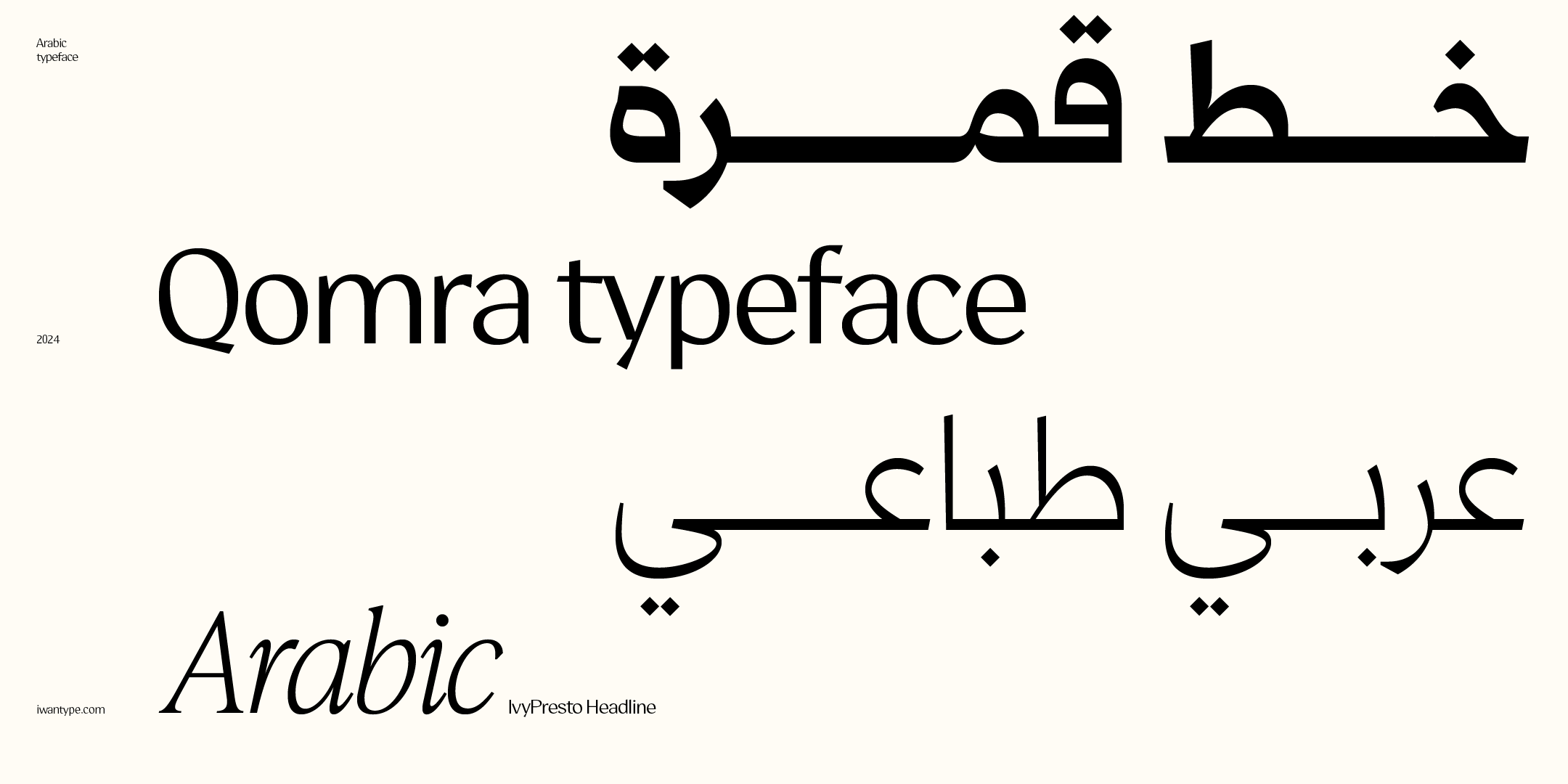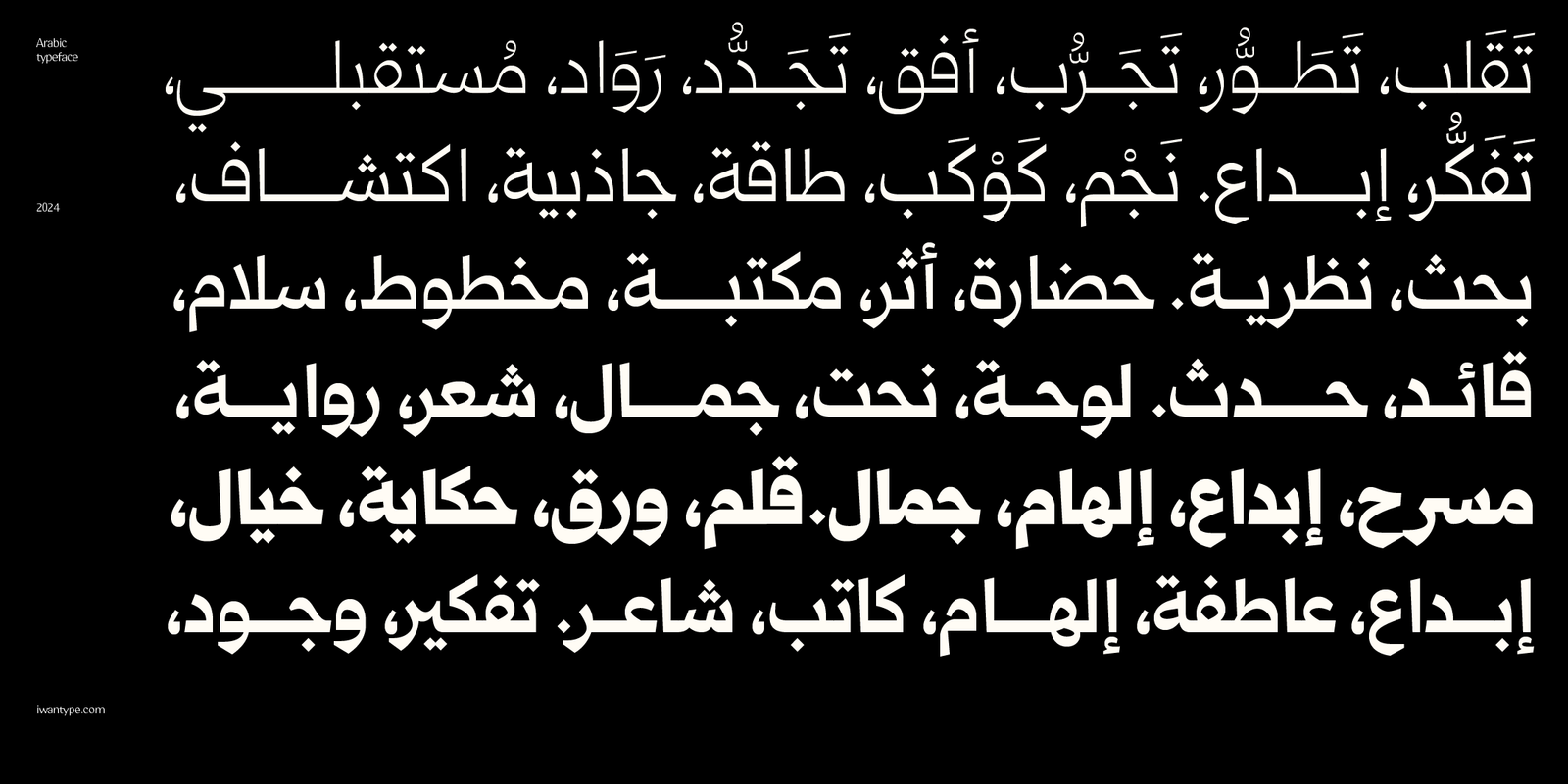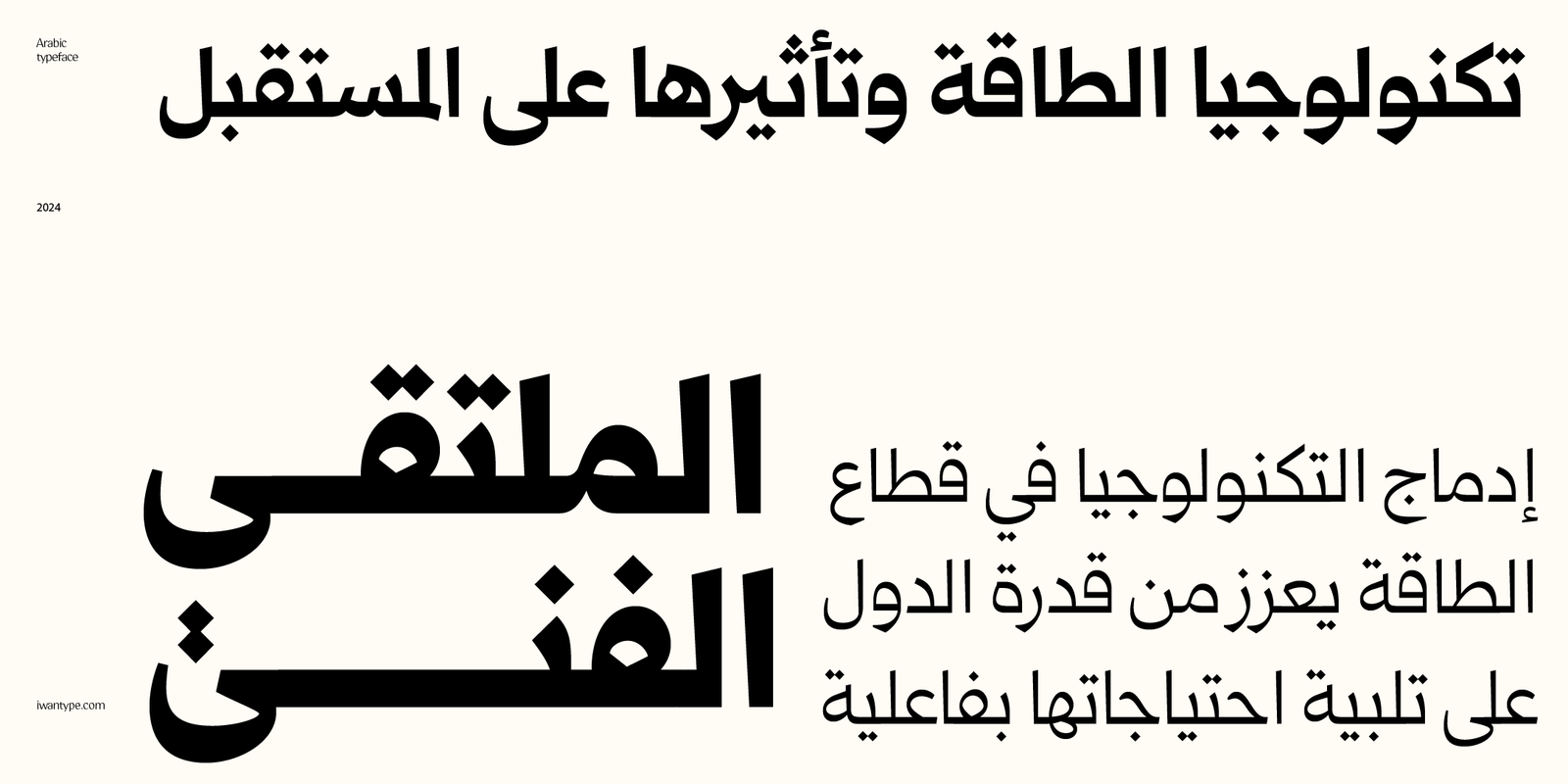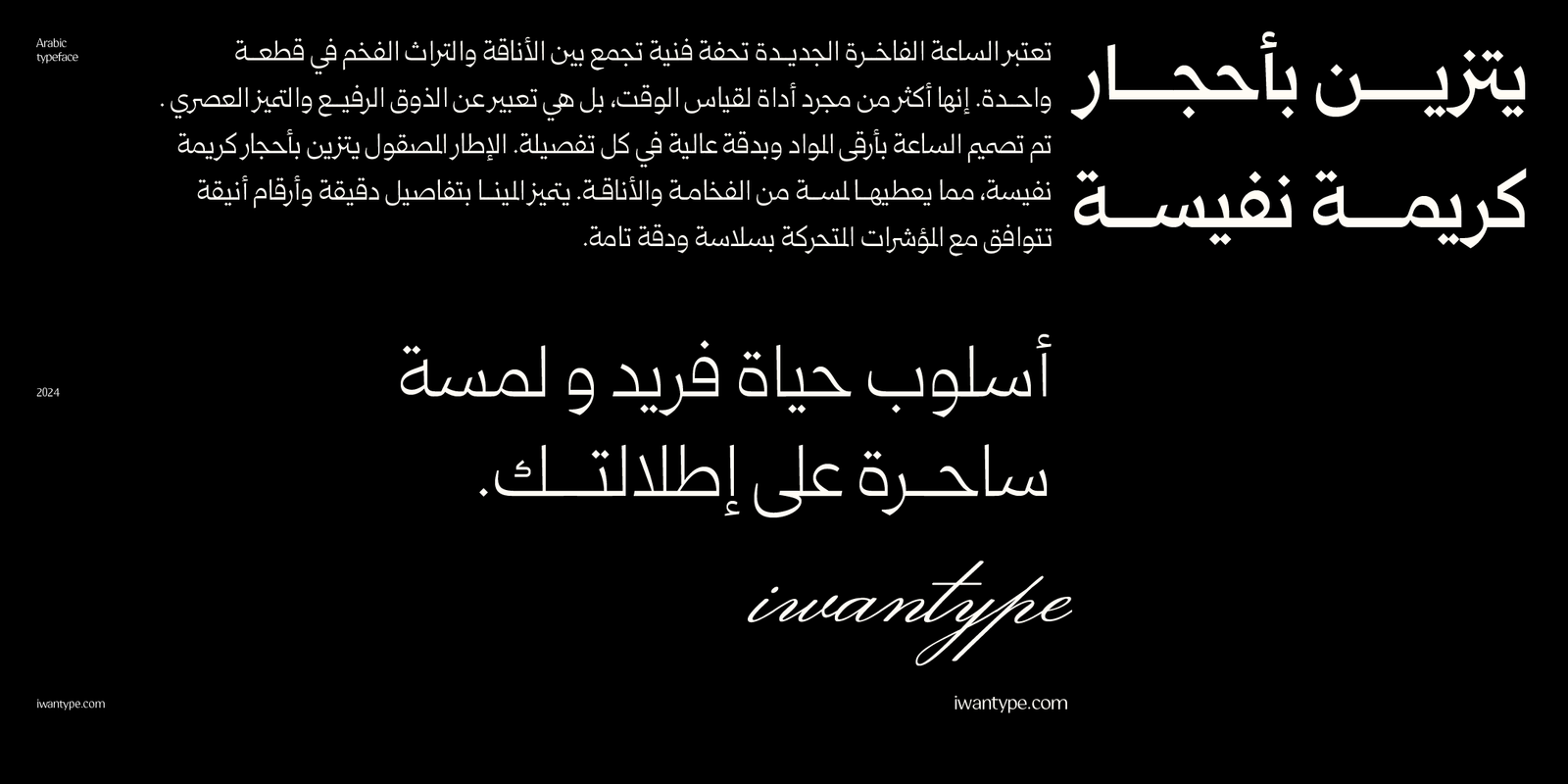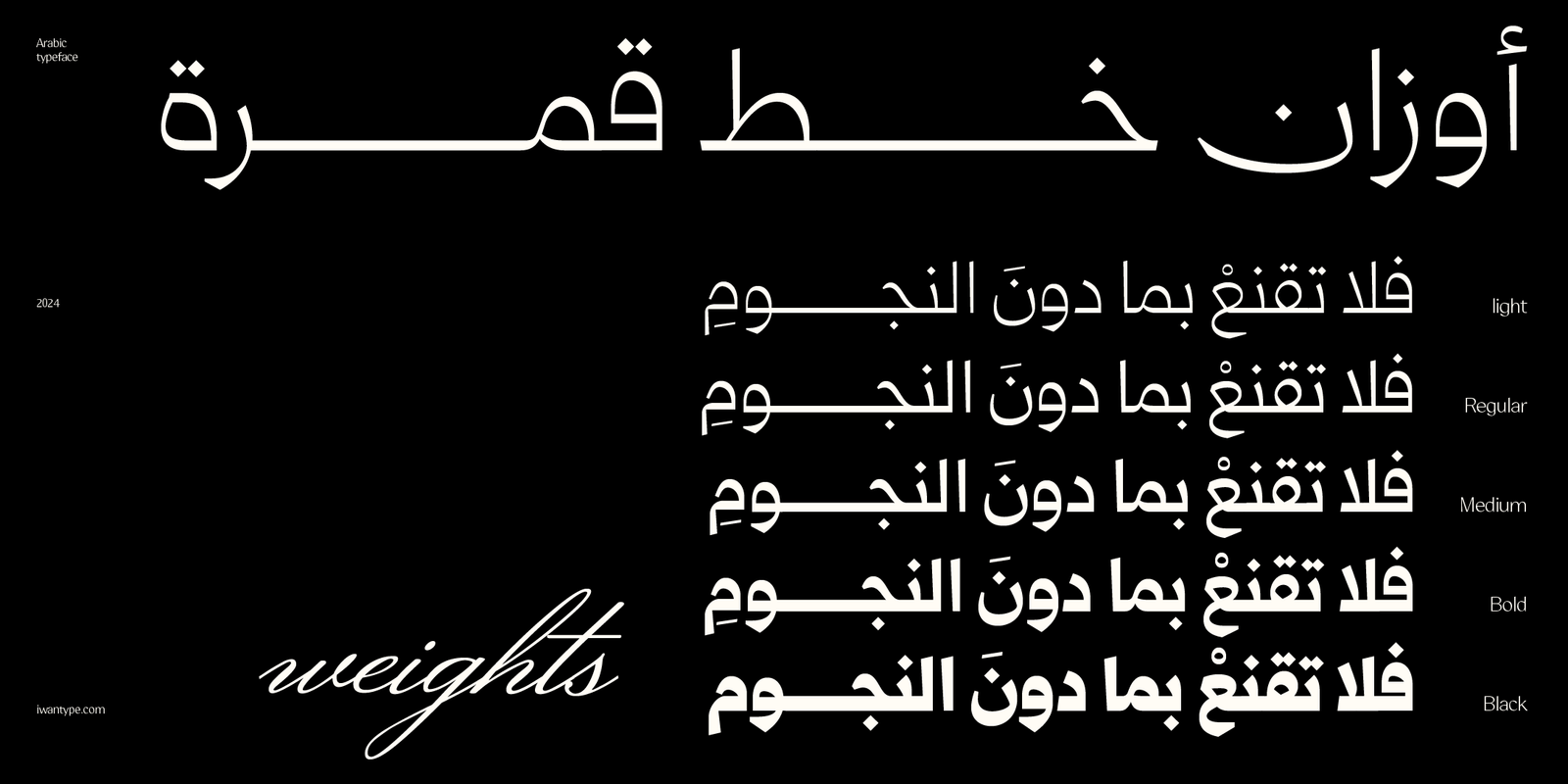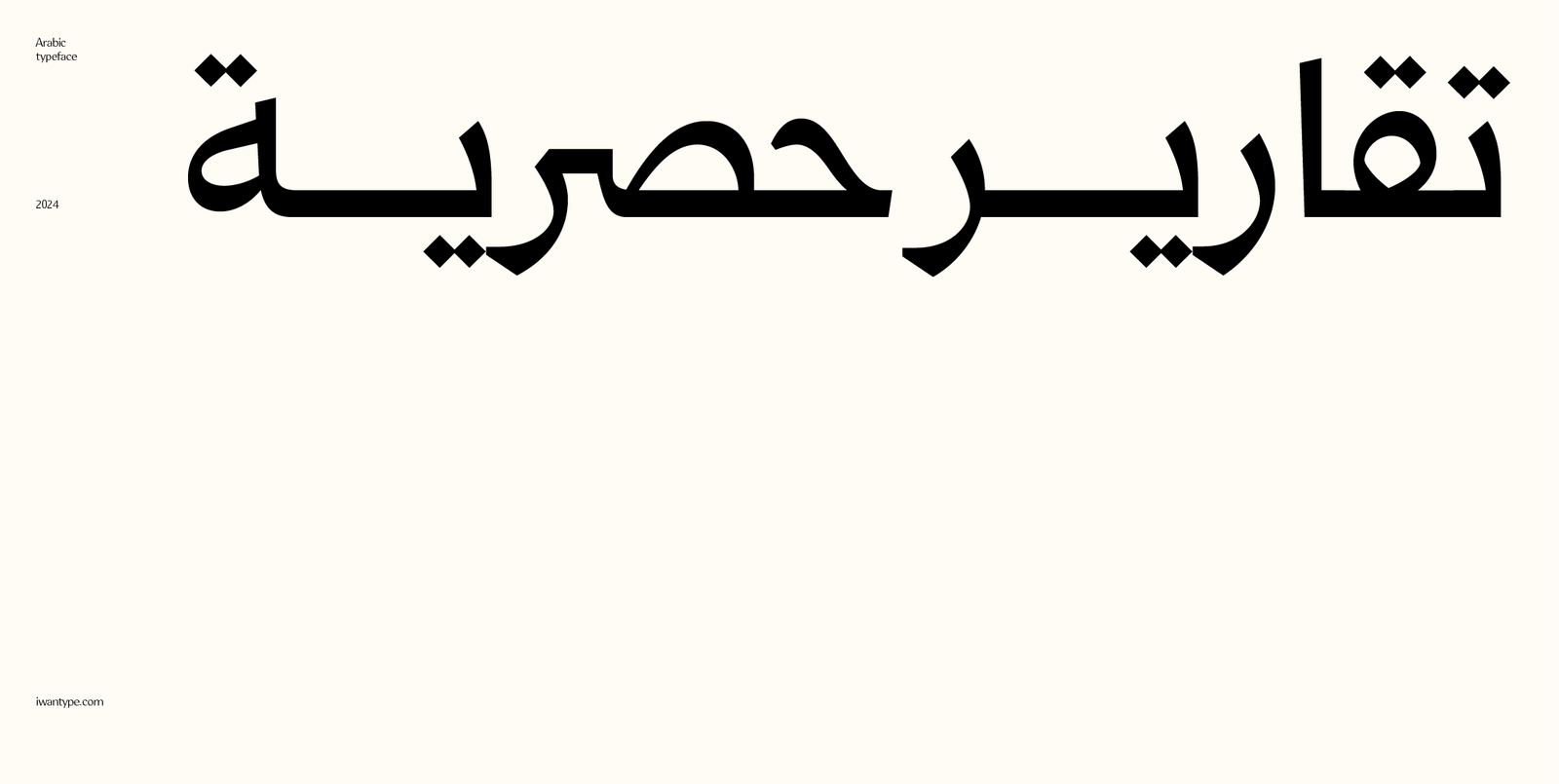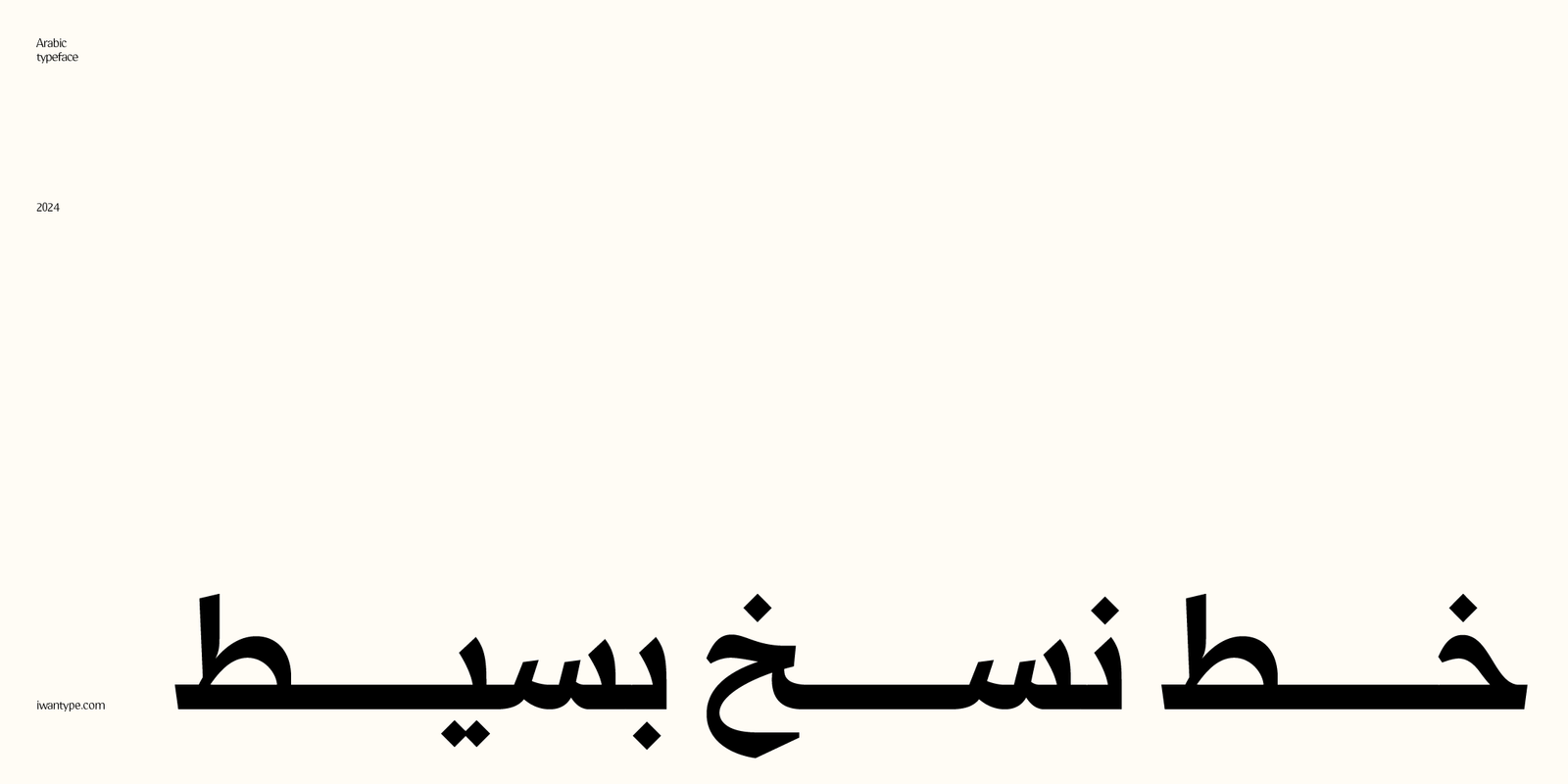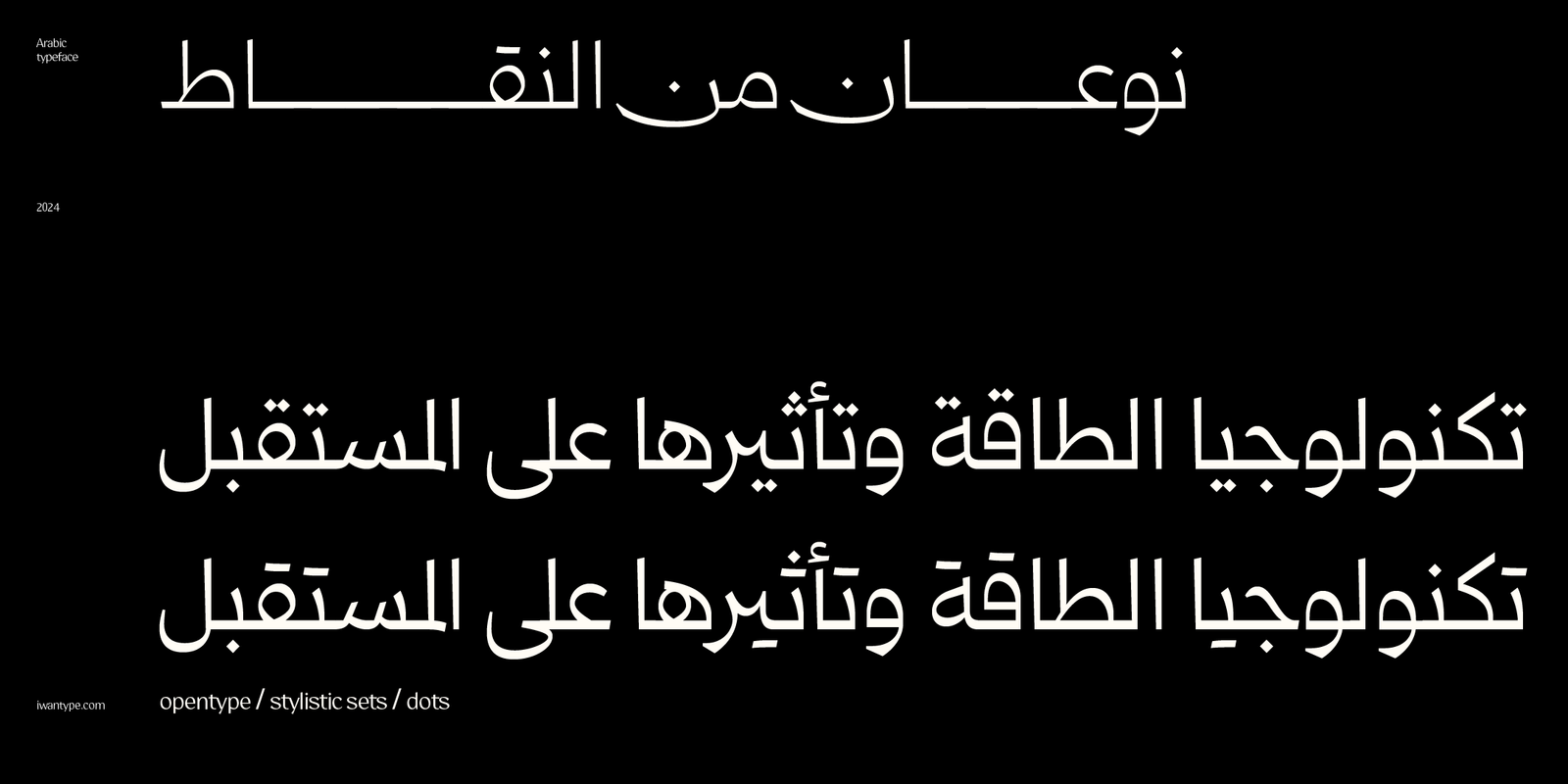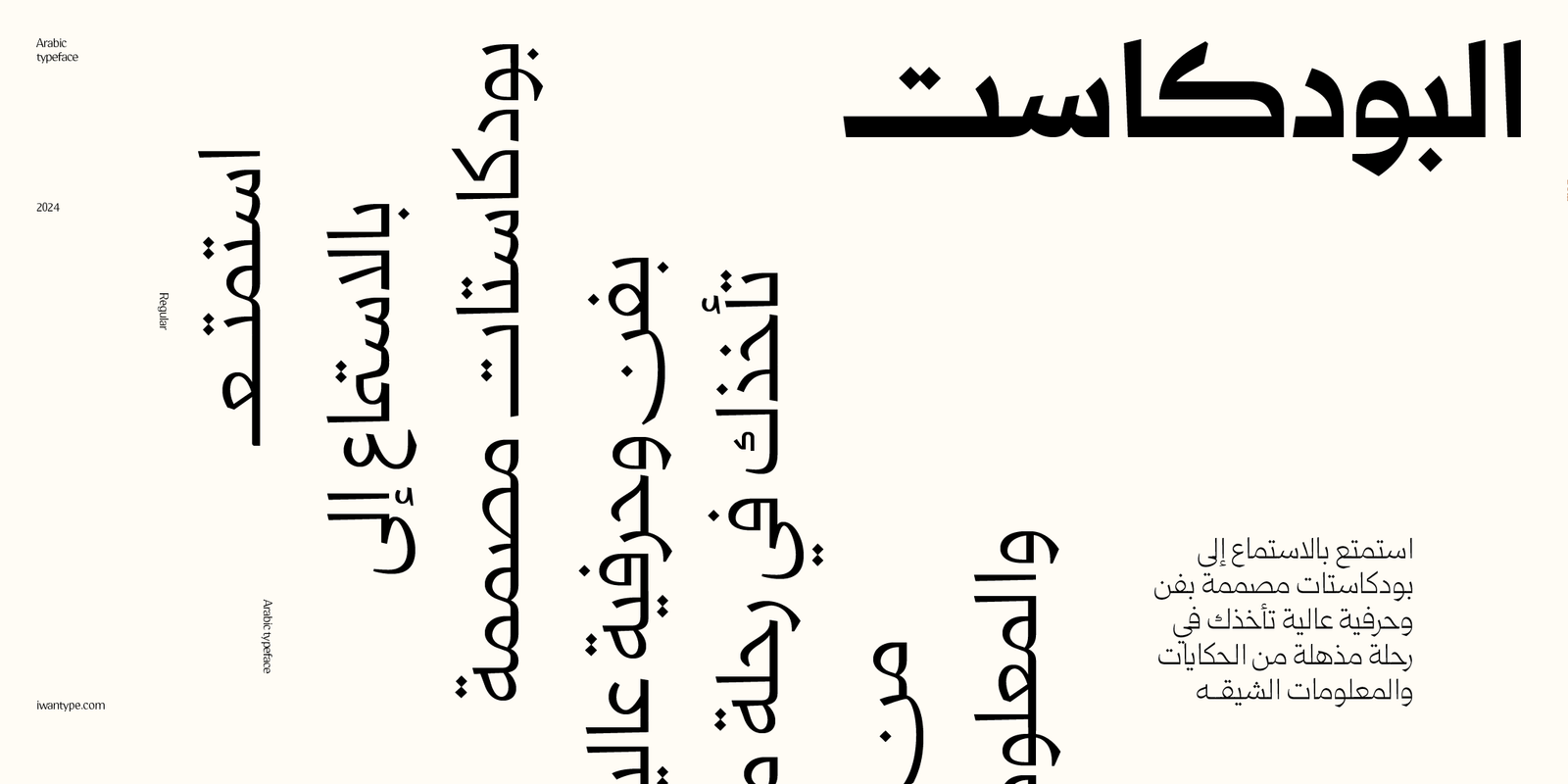
خط قمرة الطباعي – خط نسخ – Qomra Arabic typeface
الجمال في البساطة والأناقة
خط “قمرة” هو خط نسخ مسطري يجمع بين البساطة والأناقة في تصميم واحد مميز. يتميز بتفاصيله الواضحة وتصميمه الفريد، مما يجعله مثاليًا لمجموعة متنوعة من الاستخدامات.
ميزات خط قمرة:
يتضمن الخط العديد من مزايا OpenType التي تضفي عليه مرونة وتنوعًا في الاستخدام، مثل:
- أحرف مرسلة (تُفعَّل بإضافة “ءء” بعد الحرف)
- حرف ياء بنزول أقل: يقلل من نزول السطر ويعزّز انتظام النصوص.
- أحرف مركّبة تُحسّن سلاسة التراكيب وتناسق النص.
- خمسة أوزان كاملة تمنح مرونة واسعة في الاستخدام الطباعي.
- يدعم رمز الريال السعودي والريال العُماني ،ويتم تفعيلهما تلقائيًا عند كتابة الاختصارات: ر.س للريال السعودي ر.ع للريال العُماني
اللغات : عربية انجليزي